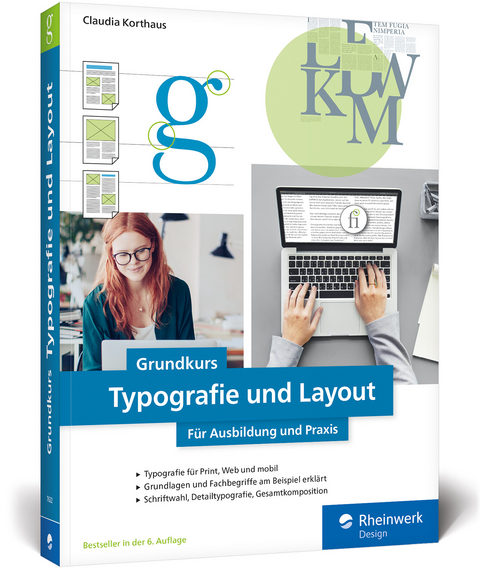
Grundkurs Typografie und Layout
Aus dem Inhalt:
- Basiswissen Schrift
- Geschichte der Schrift
- Wichtige Schriftkünstler
- Schriftwahl und Wirkung
- Buchstabe, Wort, Zeile
- Schnitte, Serifen, Ligaturen
- Größen und Abstände wählen
- Ausrichtung, Einzug, Umbruch
- Typo in InDesign und QuarkXPress
- Layouts gestalten
- Papierformat, Raumaufteilung
- Den Satzspiegel anlegen
- Text und Bild kombinieren
- ... und vieles mehr:
- Typografie im Web
- Typografie mobil
- Schreibregeln und Tipps
- Vorher-nachher-Beispiele
- Schrifttechnologien
»Dieses Buch vermittelt alle wichtigen Begriffe, Konzepte und Regeln rund um die Welt der Buchstaben und ist ein kompakter und verständlicher Einstieg in die Typografie und das Layout. Das aber nicht nur mit theoretischem Wissen, sondern auch mit praxisbezogenen Ratschlägen.« Graphische Revue Österreich 202101
»In diesem 345 Seiten starken Fachbuch wird dem Leser das Thema Typografie vermittelt. Man lernt die Regeln kennen, ohne die es oft nicht geht. Wählen Sie die richtige Schrift für ein Projekt aus, lernen Sie die Grundlagen der Seitengestaltung kennen. Das Buch vermittelt Konzepte und führt den Leser mit vielen Tipps und Anregungen zum gewünschten Ziel.«
»Die sechste überarbeitete Auflage des Klassikers [...] eignet sich neben Studium und Ausbildung auch als Nachschlagewerk für die Praxis.«
»Prima Entwürfe und originelle Ideen: Das Buch liefert Einblicke in das Geheimnis guter Gestaltung.«